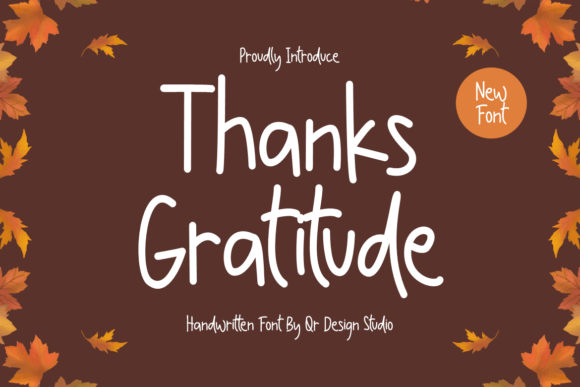
Thanks Gratitude
適切なデザイン要素を見つけるのは難しい場合がありますが、Thanks Gratitudeは作品を即座に引き立てる優れたコレクションを提供します。
POD(オンデマンド印刷)製品、結婚式の招待状、またはソーシャルメディアのグラフィックを作成している場合でも、Thanks Gratitudeは理想的です。